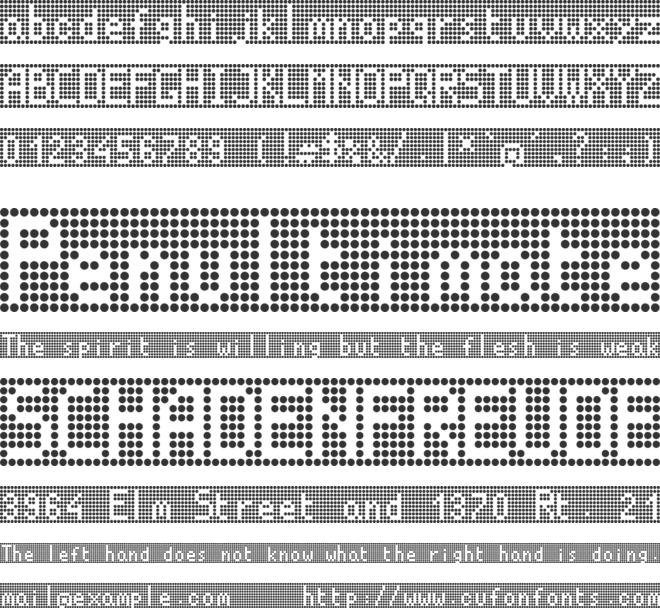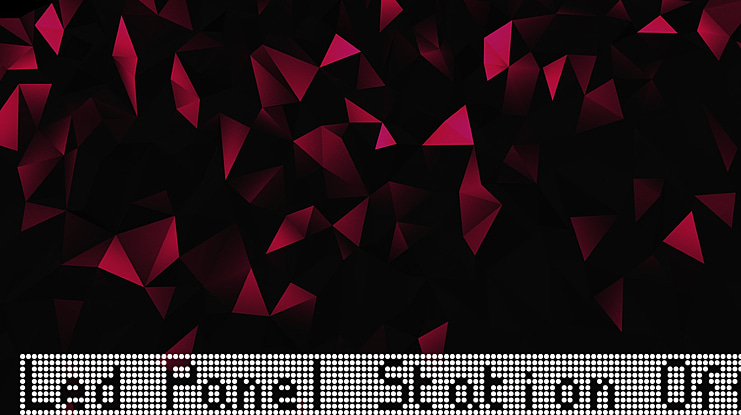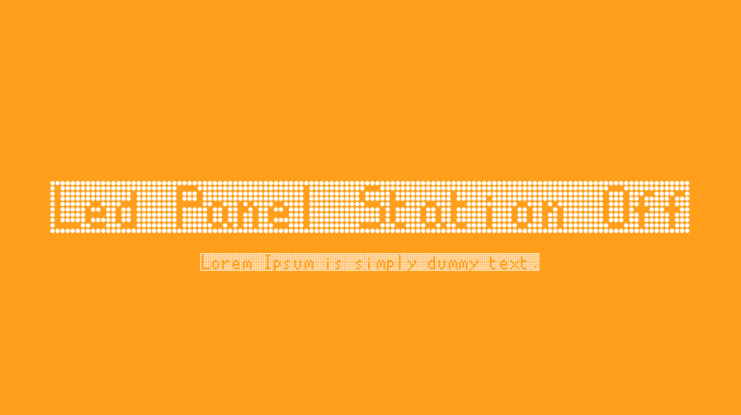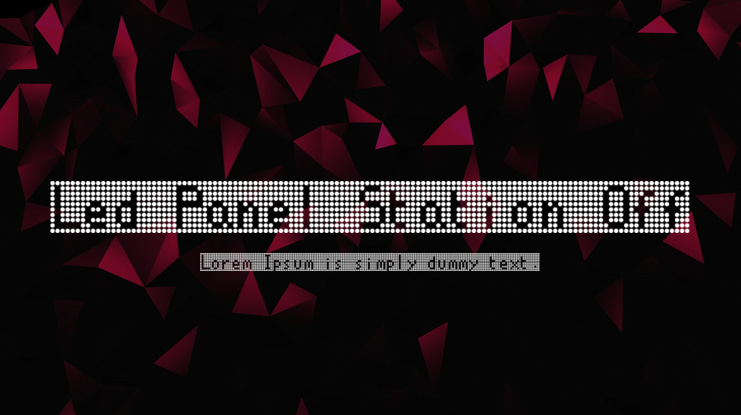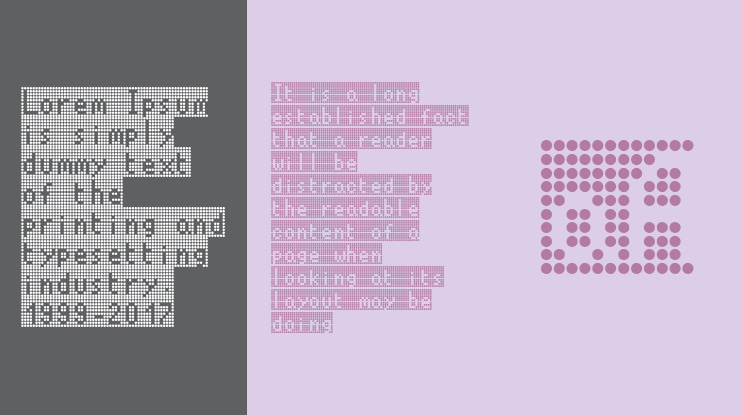
Led Panel Station Off Font
Police inspirée des anciens panneaux d'affichage de gares et aéroports.
Existe en version ON, et en version OFF. Idéal Wordart, affiche...
Font inspired by old station and airport billboards.